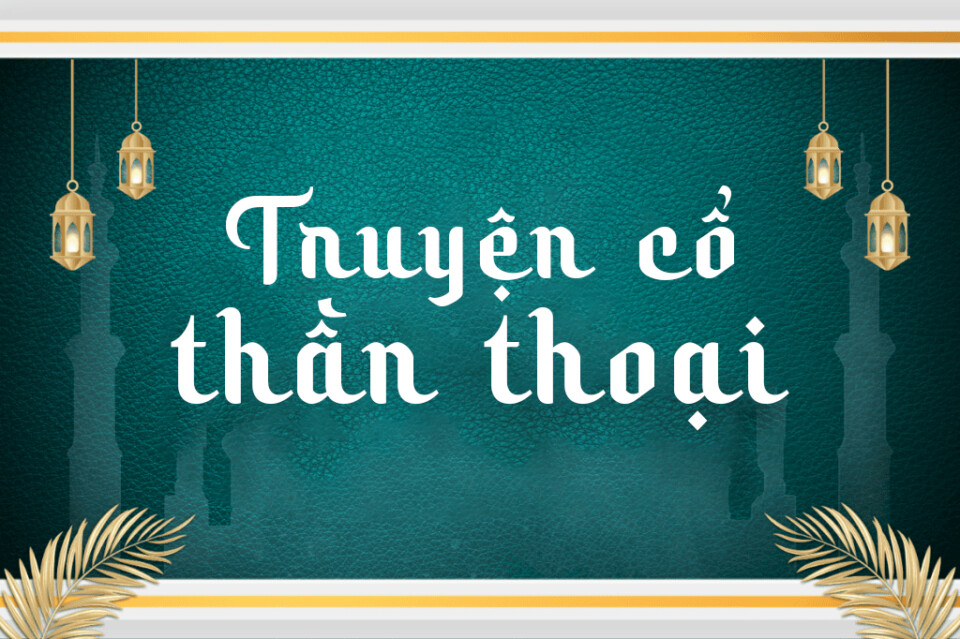
Font Việt hóa 1FTV Sacred Ramadhan
Giới thiệu về bộ Font Việt hóa 1FTV Sacred Ramadhan
Trong thế giới đồ họa hiện đại, việc tìm kiếm một bộ Font Miễn Phí mang đậm bản sắc văn hóa nhưng vẫn giữ được nét thanh lịch là điều vô cùng cần thiết. Font Việt hóa 1FTV Sacred Ramadhan chính là sự lựa chọn hoàn hảo cho những ai đang tìm kiếm phong cách thư pháp Ả Rập cách điệu. Đây là bộ phông chữ được tinh chỉnh kỹ lưỡng, giúp các nhà thiết kế Việt Nam dễ dàng thể hiện nội dung mà không lo lỗi dấu tiếng Việt, mang lại vẻ đẹp huyền bí và trang trọng cho mọi dự án nghệ thuật.
Đặc điểm nổi bật của font chữ
Bộ Font Việt hóa 1FTV Sacred Ramadhan sở hữu những đường nét uốn lượn tinh tế, mô phỏng phong cách chữ viết tay truyền thống của vùng Trung Đông. Các ký tự được thiết kế với độ tương phản cao, tạo nên sự uyển chuyển nhưng vẫn rất mạnh mẽ. Điều này giúp bộ font cực kỳ phù hợp cho các tiêu đề lớn, banner sự kiện văn hóa hoặc các thiệp mời mang phong cách tôn giáo, tâm linh.
Ứng dụng thực tế của Font Việt hóa 1FTV Sacred Ramadhan
Sáng tạo trong học tập và thiết kế
Đối với các bạn học sinh và giáo viên, việc sử dụng Font Việt hóa 1FTV Sacred Ramadhan trong các bài thuyết trình về lịch sử thế giới hoặc văn hóa phương Đông sẽ tạo nên sự khác biệt rõ rệt. Bộ font giúp bài làm trở nên sinh động và chuyên nghiệp hơn, thu hút người xem ngay từ cái nhìn đầu tiên.
Lưu ý khi sử dụng font
Mặc dù bộ font có tính thẩm mỹ rất cao, người dùng nên ưu tiên sử dụng cho các đoạn văn bản ngắn hoặc tiêu đề chính. Việc lạm dụng vào các đoạn văn dài có thể làm giảm khả năng đọc. Bạn nên kết hợp nó với các phông chữ không chân đơn giản để tạo ra sự cân bằng cho tổng thể bố cục thiết kế.